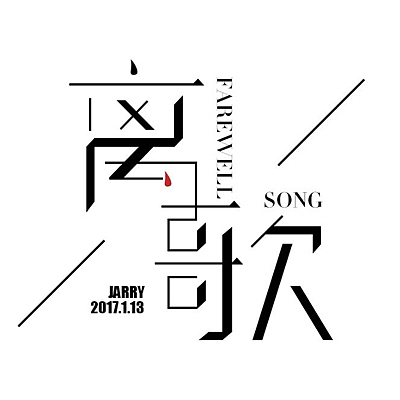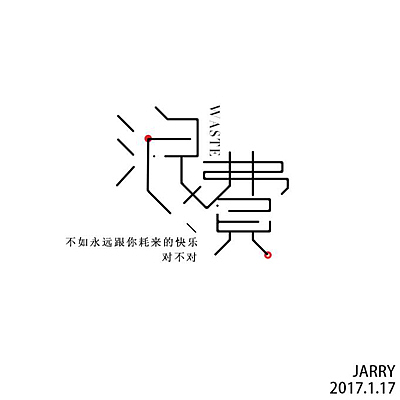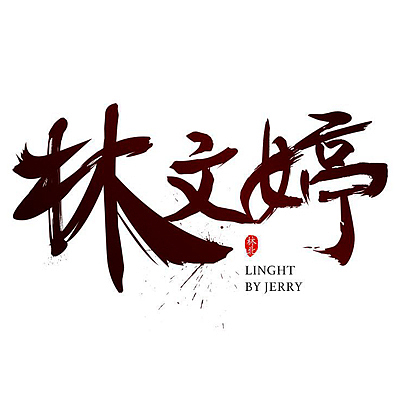
字体设计-新手练习
业余时间做的一点点字体练习,甚至都谈不上设计吧,还是很喜欢做字体的感觉,字体里面包含了很多感情在里面,好的坏的,无声的宣泄,做完之后,神清气爽。。。
分离是为了更好的在一起,合适在一起是幸福,不合适在一起更多的是难过,说不合适只不过是不爱了,也有道理,但不是每个人内心都足够强大,水滴石穿,再坚强,是不是也会被点点滴滴的瓦解。
和你在一起,不算浪费。
毛笔字体很难驾驭,做了一些之后提升并不明显,只能慢慢来了,笔墨间传达出来的感觉,还是很喜欢的。